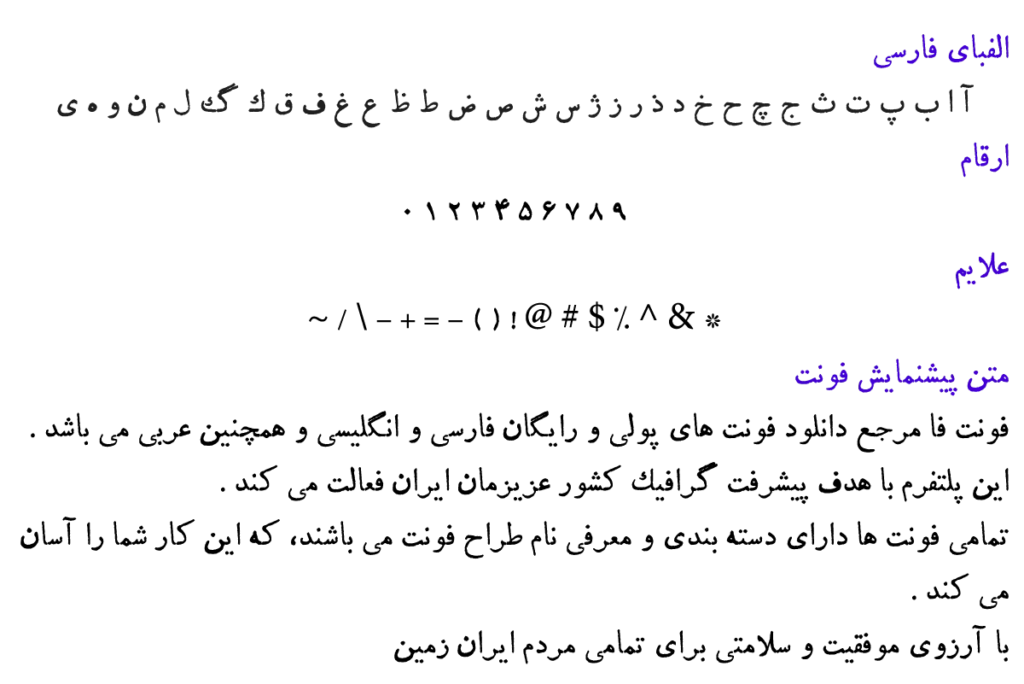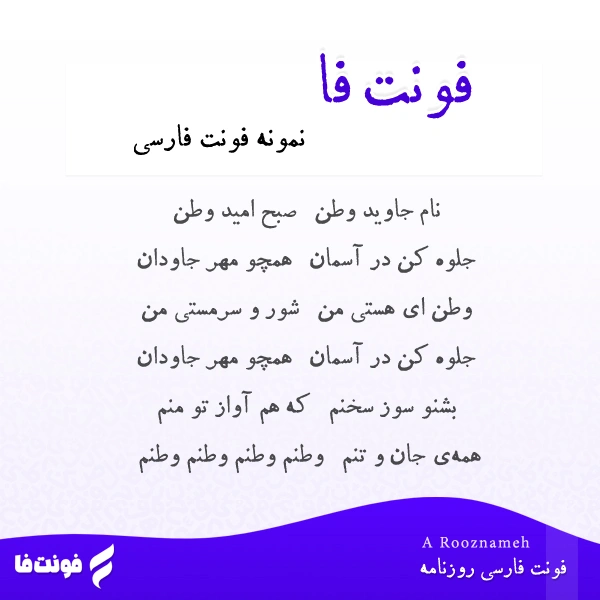
فونت فارسی روزنامه – A Rooznameh
طراح فونت: ناصر ابراهیمی نوع فونت: فونت متن
توضیحات و معرفی فونت روزنامه
فونت فارسی روزنامه ( A Rooznameh ) از مجموعه فونت های آزاد می باشد، و نیز نوع فونت متن می باشد.
فونت خوشگل مربوط توسط ناصر ابراهیمی براساس خطوط قدیمی و چاپ طراحی و ساخته شده است.
و نیز فونت A Rooznameh در یک وزن معمولی است.
- A Rooznameh Regular
در عکس زیر میتوانید جلوهای از این تایپ فیس را در قالب شعر ایرانی ببینید.